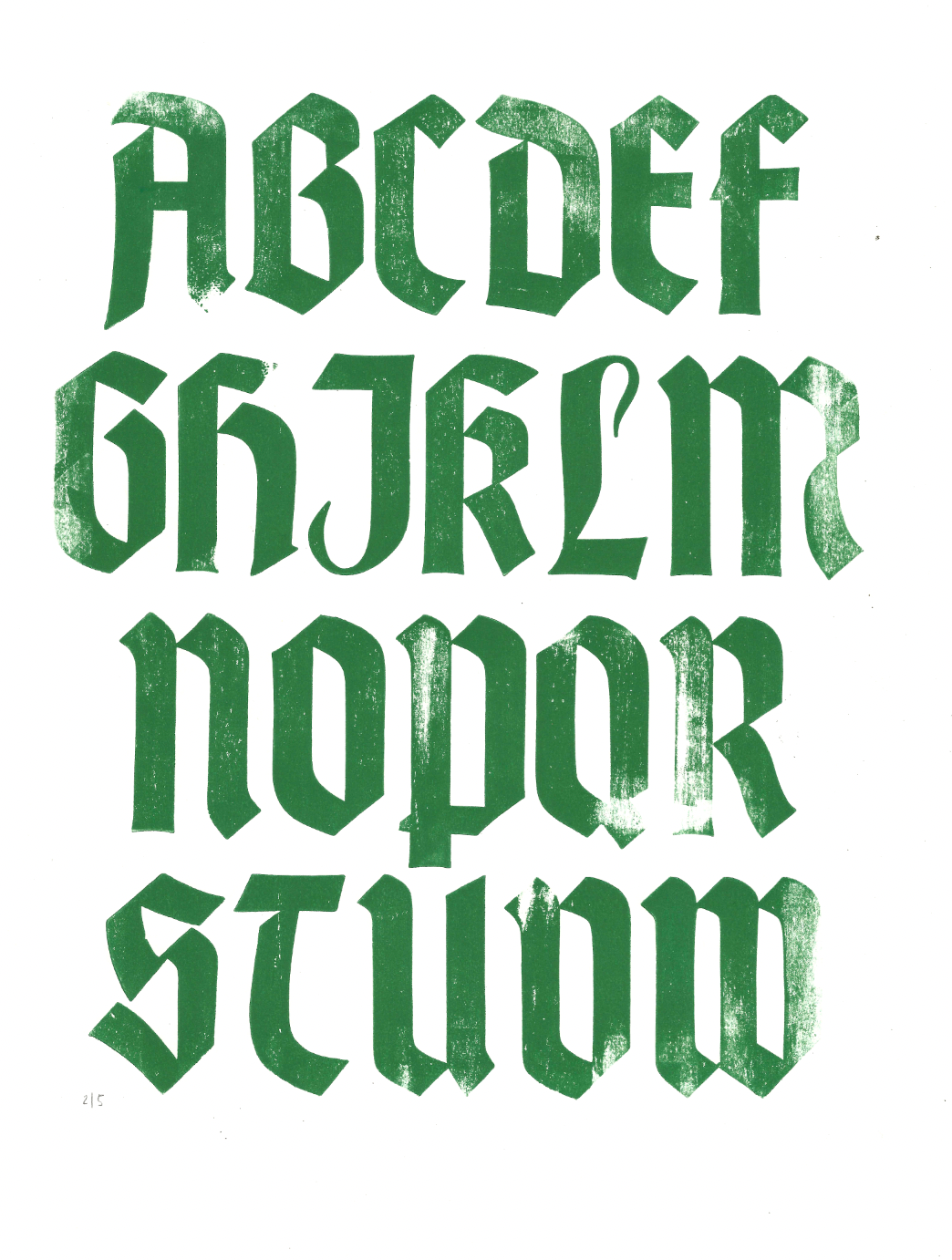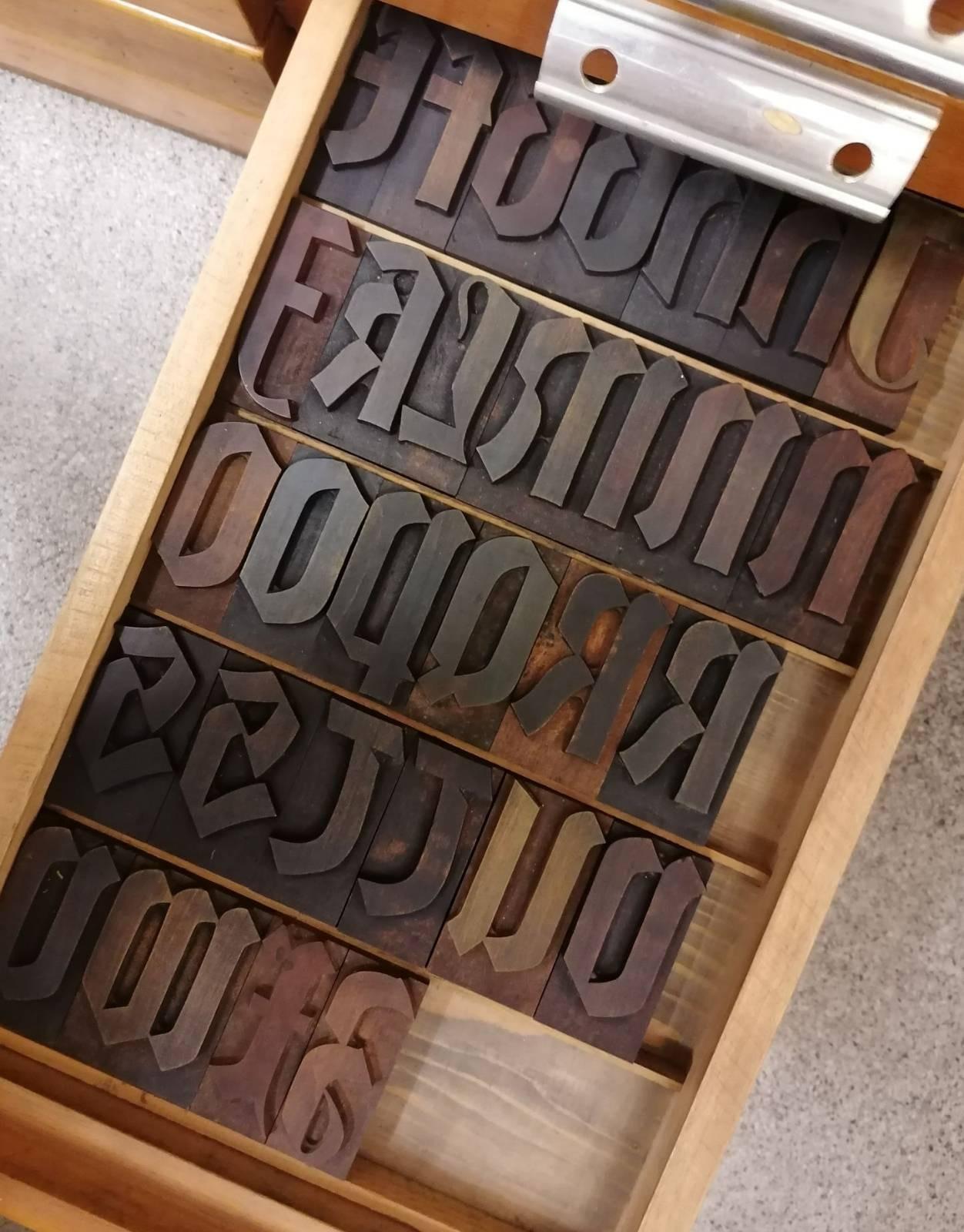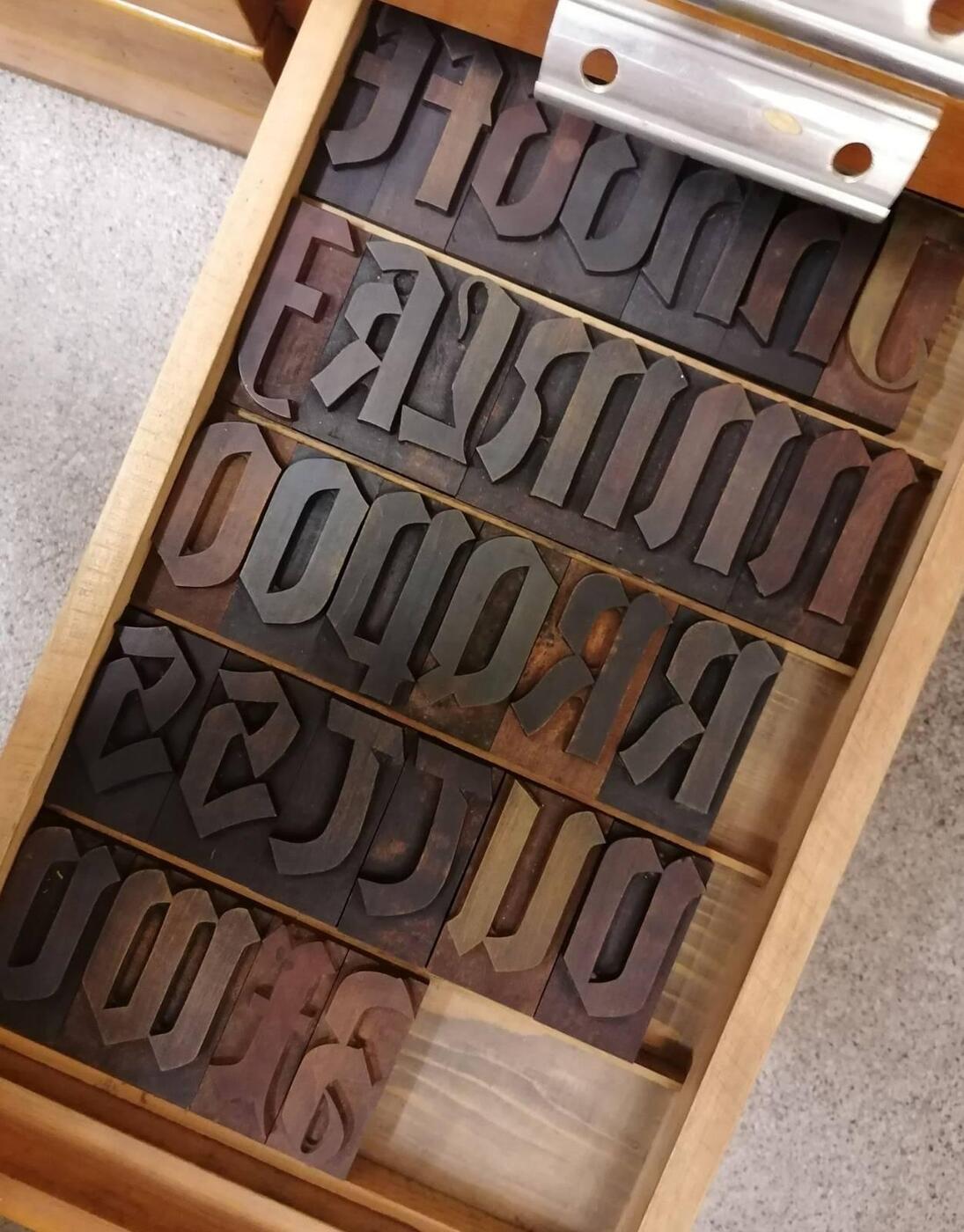
Weiß jemand mehr zu diesen gebrochenen Holzlettern?
Ich habe vor geraumer Zeit ein paar ältere Holzlettern erstanden. Jetzt würde mich sehr interssieren, ob die Schrift überhaupt einen Namen besitzt und ob es sonst noch Informationen gibt. Es sind nur Versalien vorhanden. Im Anhang ein Bild der Lettern und ein Bild von einem Testdruck.
Ich habe leider wenig Fachbücher / Unterlagen zu gebrochenen Schriften. Von der Form her würde ich sie am ehesten als Rundgotisch klassifizieren.